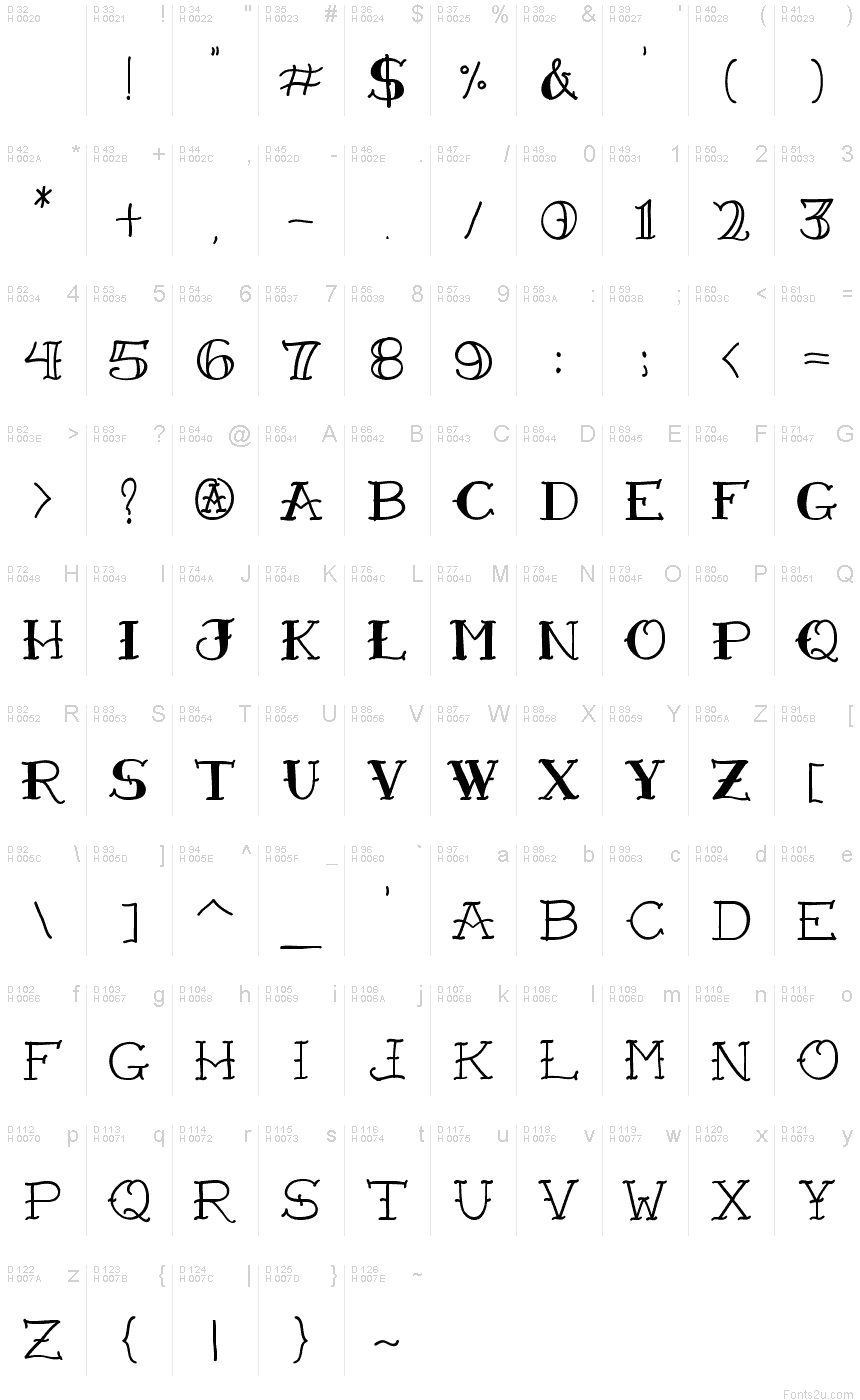
VTC Freehand Tattoo One od Larry E. Yerkes je bezplatné patkové písmo v tetovacím stylu s nepravidelným tahem ručně kreslených písmen. Jeho vysoké, široké kapitálky kombinují plynulé křivky se špičatými, čepelovitými patkami a viditelně se měnící šířkou tahů. Okraje působí dojmem, že byly vytaženy tuší ručně.
Jeho vliv staromódního tetování se hodí k vizuální identitě studií a koncertním plakátům. Ostré ozdoby se hodí také k merchandisingu kapel a obalům nápojů s temnou rockovou nebo motorkářskou tematikou. Všechna čtyři použití čerpají z písma, které funguje spíše jako ilustrovaný tetovací motiv než jako běžný tištěný typ.